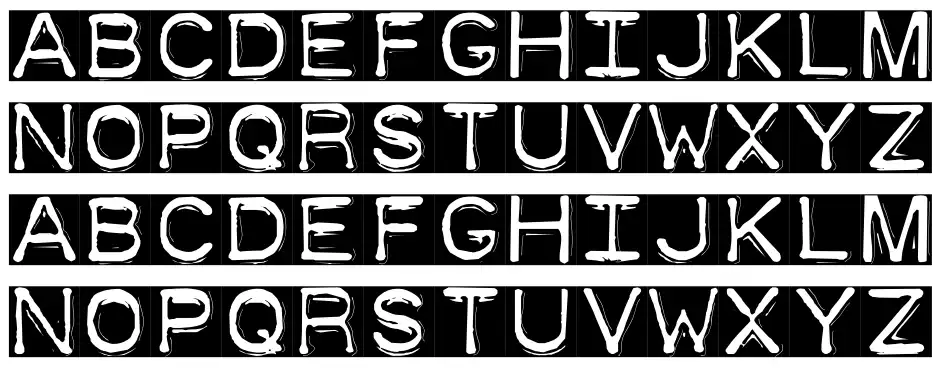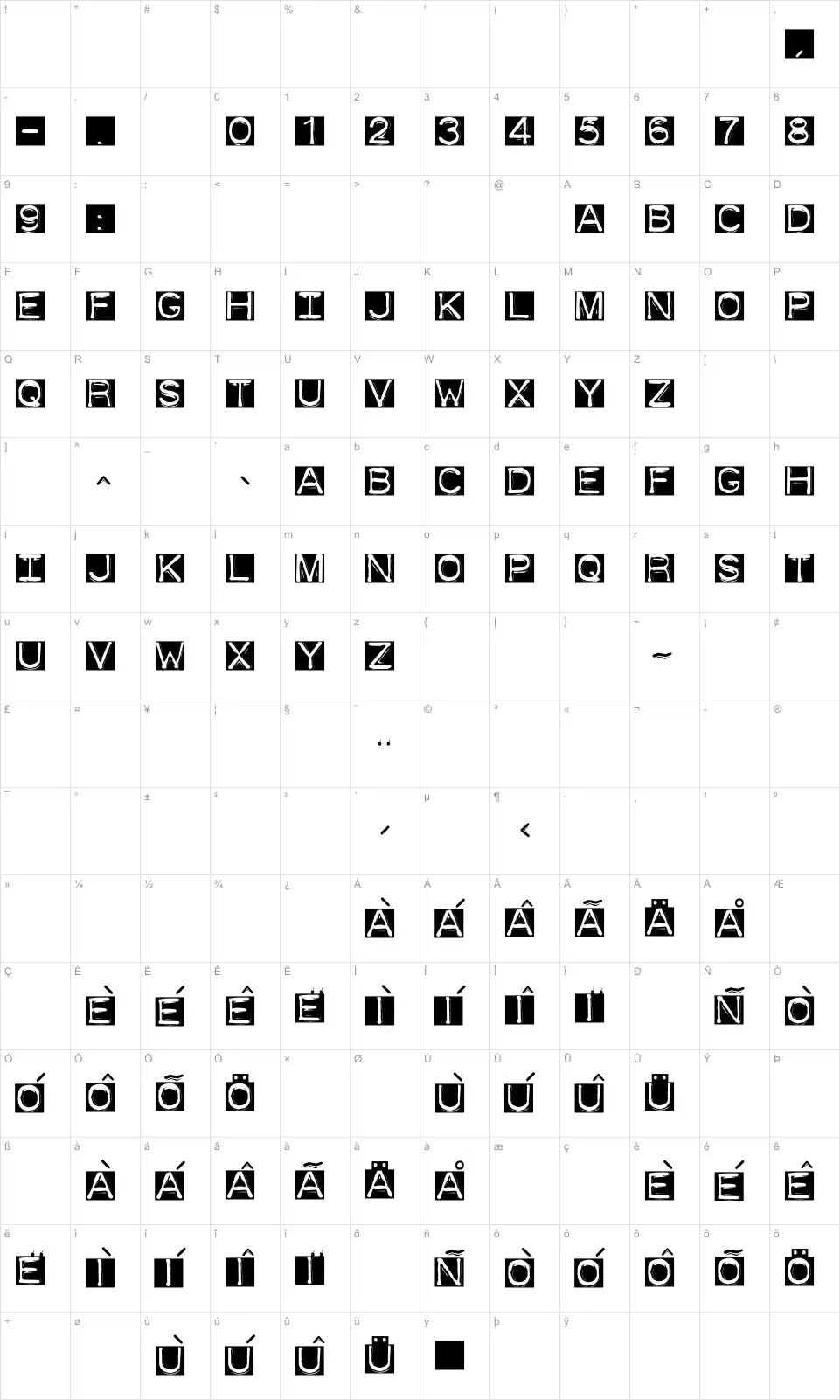
A fonte Dymo Font Invers, criada pelo designer Manfred Klein, oferece um toque sofisticado e impecável para textos e layouts. Com sua categoria ‘Fancy’, ela é perfeita para adicionar um toque único e elegante a qualquer projeto. Se você está procurando por essa fonte ou quer ver como ela se assemelha a texto personalizado antes de implementar, o Dymo Font Invers pode ser baixada ou gerado online. Com sua licença gratuita e tamanho de arquivo compacto de apenas 23 KB, ela é um recurso atraente para qualquer designer gráfico em busca de um visual chamativo e original. Adicionada em 12 de julho de 2022, a fonte já tem mais de 7380 downloads, demonstrando seu valor e popularidade. Visite o website do designer, [https://manfred-klein.ina-mar.com](https://manfred-klein.ina-mar.com), para explorar mais de seus trabalhos.
Categoria: Fancy › Decorative
Designer: Manfred Klein